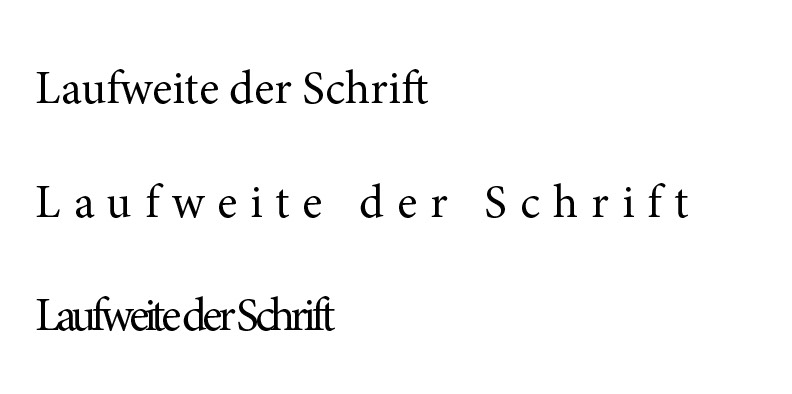
Typografie-Grundlagen
Schrift wirkt. Ob Website, Speisekarte, Plakat, Visitenkarte, Artikel – überall dort, wo man mit Text arbeitet, transportiert man nicht nur Informationen, sondern erzeugt eine bestimmte Wirkung, bewusst oder unbewusst, positiver oder negativer Art.
Aus diesem Grund wollen wir uns in einer kleinen Serie näher mit den Typografie-Grundlagen beschäftigen und Ihnen eine Reihe von Tipps und Basics an die Hand geben, damit Sie Ihre Drucksachen noch bewusster und wirkungsvoller gestalten können.
„Eine Schrift wirkt immer“
Eine Schrift wirkt immer – sie tut es mit ihrer Form, ihrer Stärke, ihrer Breite, ihrem Stil, ihrem Duktus, ihrer Ausstrahlung. Gute Typografie ist nicht nur die Kunst, den Text lesbar zu gestalten, sondern auch, die Schrift als Gestaltungselement einzusetzen, sie zu arrangieren und den Inhalt optimal zu transportieren.
Dazu zählt erstens und ganz entscheidend die Wahl der richtigen, also der für diese Zwecke, für diesen Inhalt, für diese Größe, für diese Menge und für diese Leseumstände optimale Schriftart; im zweiten Schritt muss die richtige Schrift anschließend auch so verwendet werden, dass sie optimal arbeiten kann. Dafür sind passende Größenverhältnisse von Schrift und Räumen wie dem Zeilenabstand oder der Laufweite nötig, optimale Zeilen- und Spaltenbreiten, aber auch der optimale Einsatz von verschiedenen Schnitten, um beispielsweise bestimmte Satzteile oder Absätze hervorzuheben.
Fünf grundlegende Tipps für gute Typografie
1. Beachten Sie die Wirkung der Schrift
Jede Schrift wirkt und spricht die Emotionen des Betrachters an. Beachten Sie diese Wirkung, wenn Sie sich für eine Schrift entscheiden. Gleichen Sie die Wirkung der Schrift mit Ihrer gewünschten Außenwirkung ab. Grundsätzlich genügen zwei verschiedene Schriften pro Gestaltung; auch eine Schrift kann vollends ausreichend sein.
Schon dieses einfache Beispiel zeigt: Schriften können völlig unterschiedlich wirken und die Kernbotschaft in eine bestimmte Richtung lenken
2. Suchen Sie die Schrift nach Ihrem Einsatz aus
Achten Sie also neben der emotionalen Wirkung einer Schrift auch auf deren praktische Einsatzmöglichkeiten. Die Lesbarkeit einer Schrift kann sich mit ihrer Größe verändern. Lässt sie sich in der Größe, in der Sie sie verwenden werden, optimal lesen? Ist sie für Ihren Mengentext geeignet? Wenn Sie verschiedene Auszeichnungsmöglichkeiten im Text benötigen, achten Sie auf eine Schrift mit genügend Schnitten, also Varianten für kursiv, fett etc.
Wird oft unterschätzt: Der Platzbedarf von Fonts kann stark variieren, selbst bei gleicher Schriftgröße (Hintergründe dazu im Artikel Schriftgrößen-Einmaleins)
3. Mischen Sie Schriften mit Bedacht
Achten Sie auf die Mischung. Wer zwei für den Inhalt optimal passende Schriften ausgewählt hat, ist noch nicht auf der sicheren Seite. Auch wenn die beiden Schriften vielleicht hervorragend für den Inhalt geeignet sind, müssen sie sich auch miteinander gut verstehen, sonst nutzt die beste Vorauswahl nichts. Vermeiden Sie das Mischen von Schriften, die sich gegenseitig den Rang ablaufen; in der Regel sollte einer Schrift der Vorrang gewährt werden, die andere Schrift sollte sich mit dem Platz im Hintergrund zufriedengeben.
4. Sorgen Sie für den richtigen Kontrast
Weiße Schrift auf weißem Papier – schwer lesbar. Ein schwarzer oder dunkler Buchstabe auf weißem oder hellem Hintergrund oder umgekehrt, das ist lesbar. Lesbarkeit entsteht also im ersten Schritt durch Kontrast. Der weiße Raum im und um den Buchstaben ist also wesentlich für das Gesamtbild. Die Abstände der Buchstaben zueinander, die Abstände der Zeilen zueinander, letztlich auch die Abstände der Textzeile zum Papierrand, all das erhöht oder verringert die Lesbarkeit genauso wie der Einsatz von Farbe.
5. Setzen Sie Zeichen
Achten Sie auf korrekte Zeichensetzung. Ein Trennstrich ist etwas anderes als ein Gedankenstrich, und Zollzeichen sind keine Anführungszeichen. Für jeden gewünschten Ausdruck gibt es ein passendes Zeichen – Sie müssen es nur richtig einsetzen. Auch der korrekte Einsatz von Kommas ist wesentlich und kann sogar Leben retten …
So setzt sich aus vielen Einzelteilen ein Bild zusammen, das im besten Fall dem Leser oder Betrachter auf möglichst leichte Art Informationen vermittelt und gleichzeitig genau die Gefühle anspricht, die der Gestalter erzeugen möchte.
In unserer Reihe zur Typografie betrachten wir alle einzelnen Aspekte und arbeiten uns Schritt für Schritt zu einem optimalen Einsatz des Gestaltungsmittels Schrift. Los geht es mit den Themen „Geviert und Kegel“, der am 28. November erscheint.
Typografie-Grundlagen-Glossar
Antiqua Serifenschriften, die auf der Form der römischen Capitalis beruhen
Ausrichtung Textausrichtung bezeichnet die Satzart wie linksbündig, rechtsbündig oder Blocksatz
Außensteg Bei Doppelseiten: freier Raum zwischen der Satzspiegelaußenkante und der Papierkante
Auszeichnung Das Verändern und Hervorheben einzelner Textabschnitte oder Zeichen
Blocksatz Eine Ausrichtungsart, bei der alle Zeilen bis auf die letzte im Absatz links und rechts bündig enden.
Buchstabenabstand Der Abstand zwischen den einzelnen Zeichen, der die Laufweite beeinflusst und stark zur Lesbarkeit beiträgt.
Buchstabenbreite Die Breite des Buchstabens inklusive seiner Vor- und Nachbreite; auch Dickte genannt.
Divis Als Divis wird der Trennstrich bezeichnet.
Duktus Charakterzüge einer Schrift wie ihre Neigung und ihre Strichstärke bilden den Duktus der Schrift.
Durchschuss Zusätzlicher Abstand, der sich zum Zeilenabstand minus Schriftgröße addiert. Ein Zeilenabstand von 12 Punkt bei einer Schrift von 10 Punkt weist einen Durchschuss von 2 Punkt auf.
Einzug Beim Einzug wird der Text an der linken oder rechten Textkante eingerückt. Üblich ist ein Einzug der ersten Zeile an der linken Seite, um einen neuen Absatz zu unterstreichen.
Flattersatz Textausrichtung, bei der entweder der linke, der rechte oder beide Textränder flattern; keine gleichmäßigen Achsen
Fleisch nicht druckender Bereich um den Buchstaben herum
Fraktur Schrift mit gebrochenen Rundungen
Freier Satz Ausrichtung ohne vertikale Achsen, für nur wenige Zeilen geeignet
Fußsteg Der untere, freie Bereich zwischen Papierkante und Satzspiegel
Gedankenstrich Strich in der Länge eines Halbgevierts, wird für Einschübe, aber auch als Bis-Strich, als Streckenstrich oder als Währungsstrich verwendet.
Gemeine Kleinbuchstabe
Geviert Maß in der Typografie. Das Geviert ist ein Leerraum, dessen Breite und Höhe der Kegel- bzw. Schriftgröße entsprechen. Das Geviert einer 12-Punkt-Schrift weist eine Breite und Höhe von 12 Punkt auf.
Grotesk Bezeichnung für eine serifenlose Antiqua
Grundlinie Wird auch Schriftlinie genannt. Die Linie, auf der die Mittellängen sitzen
Grundlinienraster Ein nicht druckendes Raster, das als Teil des Gestaltungsrasters, aber auch eigenständig bestehen kann. Entlang der horizontalen Linien des Grundlinienrasters verlaufen die Grundlinien des Grundtextes. Der Abstand der Rasterlinien entspricht dem Zeilenabstand des Grundtextes.
Halbgeviert Ein Leerraum im typografischen Maßsystem, das halb so breit ist wie ein Geviert. Seine Größe richtet sich immer nach der aktuellen Schriftgröße. Bei einer Schriftgröße von 12 Punkt ist ein Halbgeviert 6 Punkt groß.
Hängender Einzug Die erste Zeile eines Absatzes links bündig ausgerichtet, die Folgezeilen sind an der linken Kante um einen festen Wert eingerückt
Initial Großer, schmückender Buchstabe, der am Anfang eines Absatzes oder einer Seite steht
Innensteg Bei Doppelseiten: Abstand zwischen Bund und Satzspiegelinnenkante
Kapitälchen Eine Schriftvariante, bei der alle Buchstaben die Form von Großbuchstaben aufweisen. Die Versalien haben dabei die normale Schriftgröße, die Kleinbuchstaben sind entsprechend verkleinert.
Kegel Körper des Bleibuchstabens
Kompress Text ohne Durchschuss; ein Text in 12 Punkt Schriftgröße und 12 Punkt Zeilenabstand; das Gegenteil zu splendid.
Kursiv Ein geneigter Schriftschnitt
Kolumnentitel Zeile mit Pagina und /oder Text; beim lebenden Kolumnentitel wechselt der Text abhängig vom Seiteninhalt, beim toten Kolumnentitel bleibt der Text unverändert.
Laufweite Der Abstand der Zeichen zueinander
Ligatur Eine Verbindung zwischen mindestens zwei Buchstaben zu einem Zeichen, beispielsweise zwischen dem ff, fl oder ft.
Majuskel Großbuchstabe
Mediävalziffer Ziffer mit Ober- bzw. Unterlänge sowie unterschiedlicher Breite, die sich harmonisch ins Schriftbild einfügt
Minuskel Kleinbuchstabe
Mittelachsensatz Textausrichtung, bei der die Zeilen in der Mitte eine Achse aufweisen, von der aus die Zeilen gleichmäßig nach rechts und links flattern; wird auch als zentrierter oder symmetrischer Satz bezeichnet
Oberlänge Der obere Teil eines Buchstabens über der x-Linie, wie beim b, l oder d
Pagina Seitenzahl
Punze Innenraum eines Buchstabens wie beim o, d oder e
Rechtsbündig Textausrichtung, bei der alle Zeilen an der rechten Satzkante eine Achse aufweisen, von der aus sie nach links flattern. Nur für kurze Texte geeignet.
Registerhaltig Registerhaltiger Text liegt auf einem imaginären Grundlinienraster, wodurch der Grundtext von mehreren Spalten und Seiten deckungsgleich platziert wird.
Satzspiegel Der bedruckte Bereich einer Seite
Schriftfamilie Schriften, die auf demselben Schnitt basieren, aber in der Breite, Stärke oder Lage bzw. Neigung variieren
Schriftgrad Schriftgröße
Schriftlinie Siehe Grundlinie
Serife An-, Ab und Endstriche der Zeichen
Spationieren Ausgleichen der Buchstabenabstände; auch sperren genannt
Splendid Text mit großem Zeilenabstand; das Gegenteil zu kompress
Typometer Lineal mit dem typografischen Maßsystem
Umbruch Zusammenstellung aller Elemente zu einem Layout
Unterlänge Buchstabenbereich zwischen Grundlinie und unterem Buchstabenende
Unterschneiden Verringern der Buchstabenabstände
Versalien Großbuchstaben
x-Höhe Mittellänge
Zeilenabstand Abstand von Grundlinie zu Grundlinie